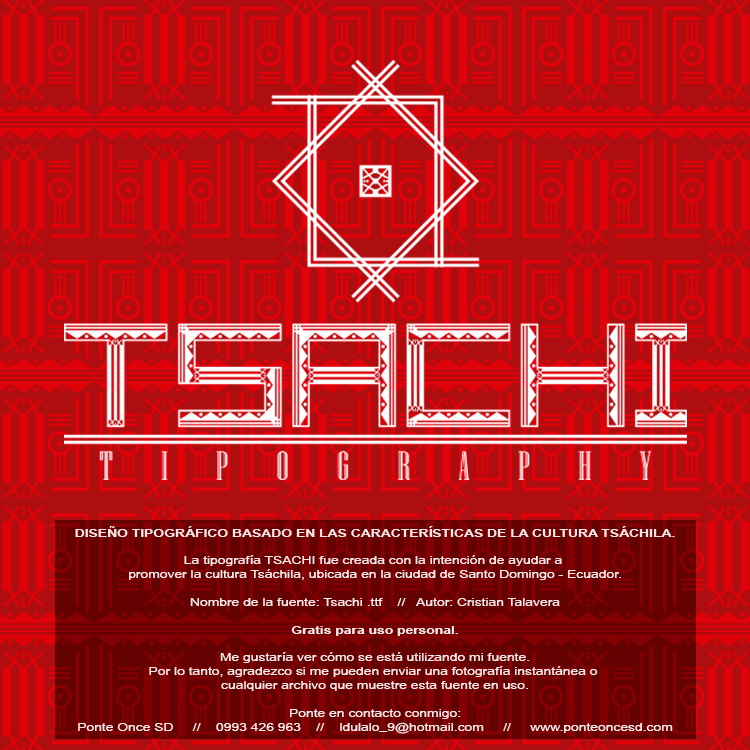
Preview and download Tsachi Font. Created by Cristian Fernando Talavera Freire in Fancy Decorative styles with 100% Free license.
DISEÑO TIPOGRÁFICO BASADO EN LAS CARACTERÍSTICAS DE LA CULTURA TSÁCHILA. La tipografía TSACHI fue creada con la intención de ayudar a promover la cultura Tsáchila, ubicada en la ciudad de Santo Domingo - Ecuador. Ponte Once SD Contactos: 0993 426 963 www.ponteoncesd.com |